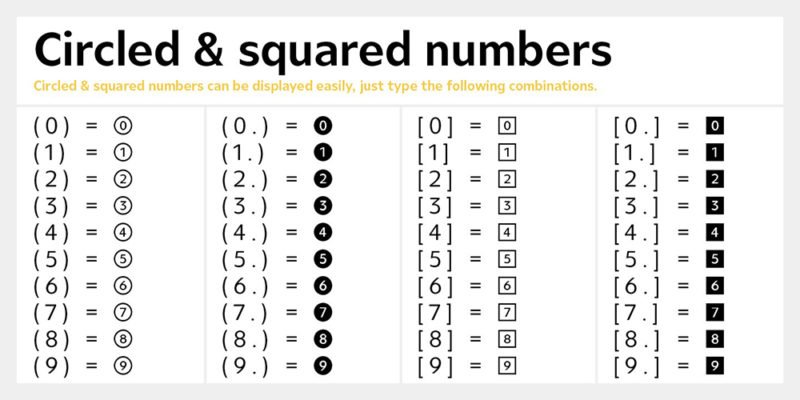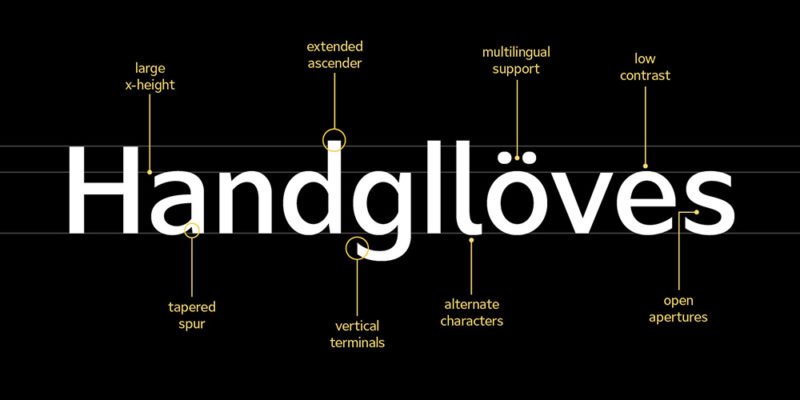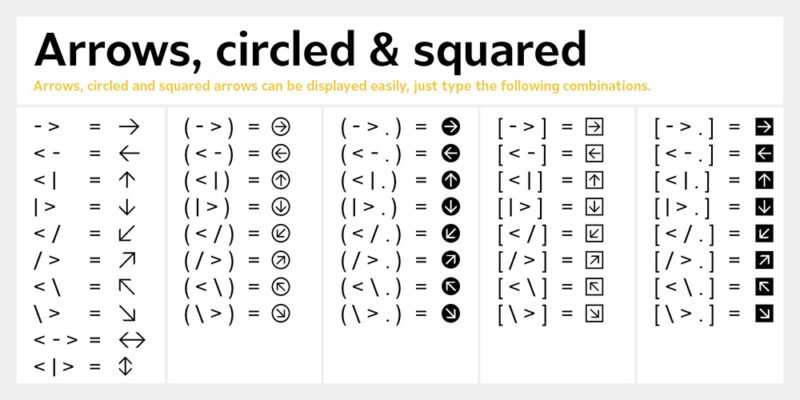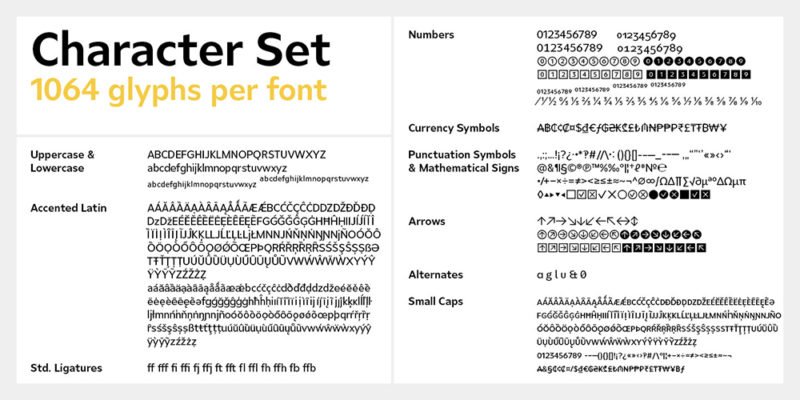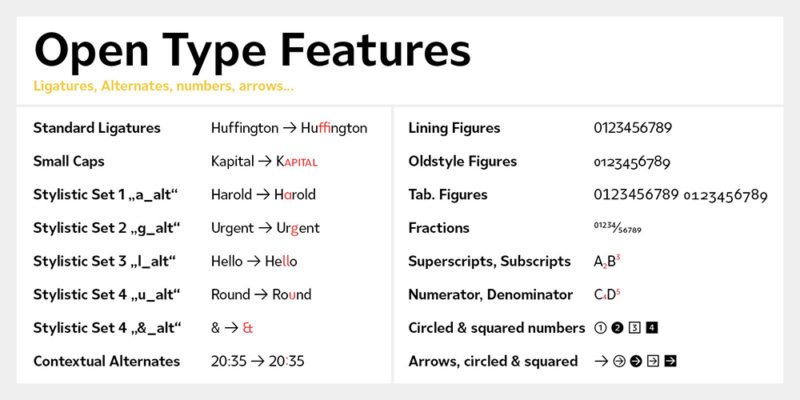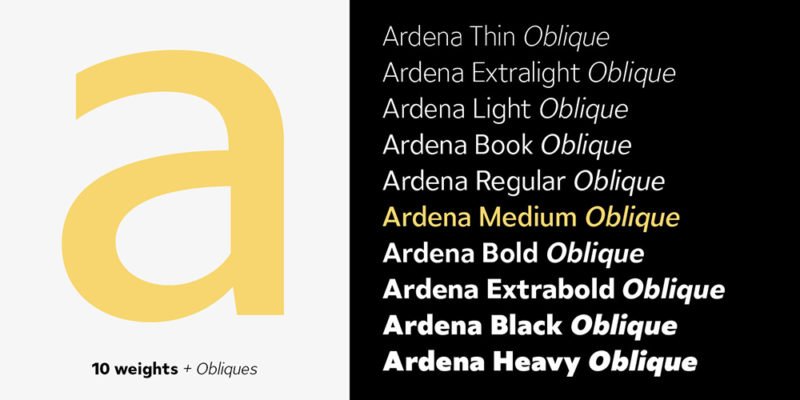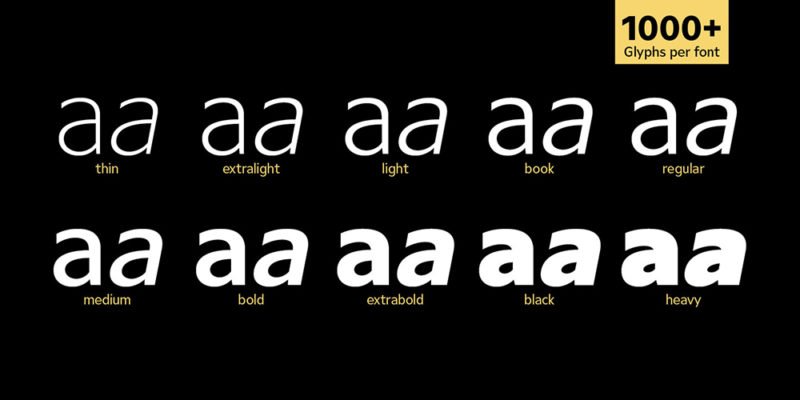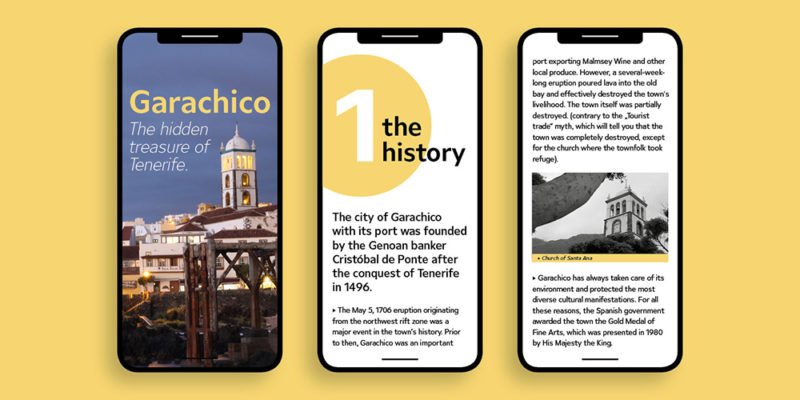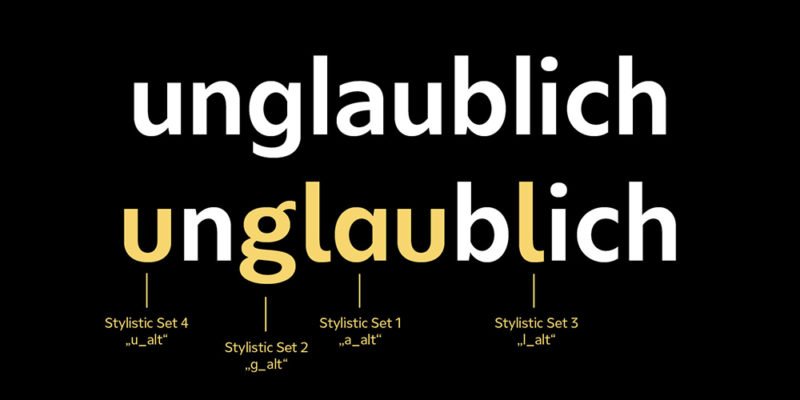
Julien Fincker firma Ardena, una tipografía de cabecera
20 estilos, 1064 glifos por fuente, más de 200 idiomas…
El diseñador galo Julien Fincker firma Ardena, una tipografía sans serif elegante, moderna, que destaca por, además de su impecable ejecución, su amplio registro de pesos, estilos, números, símbolos e idiomas. Estas características tan valoradas en la comunidad creativa, dota a la propuesta de Fincker de una versatilidad superior, postulándola como fuente de cabecera de cualquier diseñador.
«Gracias a las posibilidades del protocolo OpenType, los distintos diseños también se pueden «escribir» sin tener que seleccionarlos primero en una paleta de glifos», comenta Fischer desde su estudio en la ciudad alemana de Ditzingen.
Con Ardena, el objetivo era desarrollar una familia austera desde lo formal pero ambiciosa desde las prestaciones. Según confiesa el propio Fincker, este proyecto nació durante la búsqueda de una opción sans serif neutra y bien construida. Porque a pesar de haber encontrado miles, ninguna gozaba de la versatilidad necesaria, así es que simplemente decidió hacerla él mismo. «Comencé con los primeros bocetos y las primeras preguntas surgieron rápidamente. ¿Remates en vertical, en diagonal u horizontal? ¿Proporciones geométricas o humanísticas?, ¿curvas suaves o cónicas? Todas estas son características que pueden desarrollar su propia dinámica. Por lo tanto, no todas las sans serif son iguales a otras, como generalmente se afirma».
Acertar en la elección de una tipografía en un proyecto gráfico es comenzar con el pie derecho. Por esta razón, es de celebrar la propuesta de Julien Fincker, que desde la elegancia y la profesionalidad ha conseguido dar forma a una opción seria y viable para el éxito de cualquier composición. Estaremos atentos a más novedades.